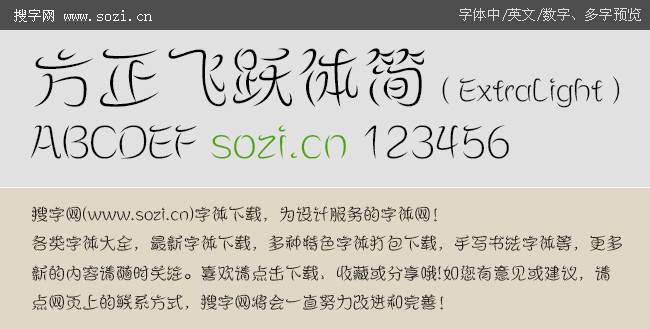
方正飛躍體簡(jiǎn)ExtraLight
搜字網(wǎng)提供一款方正飛躍體簡(jiǎn)中文字體下載,方正飛躍體簡(jiǎn)是一款充滿(mǎn)活力和跳躍的中文字體,該字體特點(diǎn)是沒(méi)有直線,全是弧線組成,橫劃都向右上角斜上,頭部有一個(gè)彎鉤,所有撇,捺,點(diǎn)都用弧線形表達(dá),因此增強(qiáng)飛躍體的感覺(jué),適合應(yīng)用于包裝設(shè)計(jì)、平面設(shè)計(jì)、網(wǎng)頁(yè)設(shè)計(jì)、海報(bào)設(shè)計(jì)等應(yīng)用。